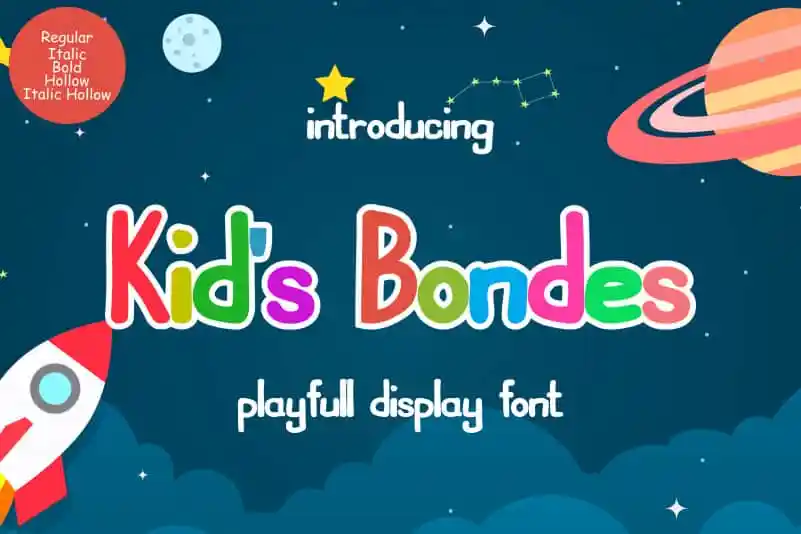
Kids Bondes Font – Download Grátis
A Kids Bondes Font é uma elegante seleção de letras manuscritas infantis que traz à tona o espírito brincalhão dos pequenos. Desenvolvida para atender a uma variedade de propósitos, incluindo embalagens de produtos, projetos de marca, revistas e postagens nas redes sociais. Este fonte irá transformar seus materiais em algo ainda mais autêntico e encantador quando usados na criação de jogos infantis ou no desenvolvimento de projetos escolares e familiares, iluminando-os com sua essência divertida e vibrante. A Kids Bondes Font é uma ótima adição para qualquer designer que busque trazer um toque único e encantador aos seus trabalhos.